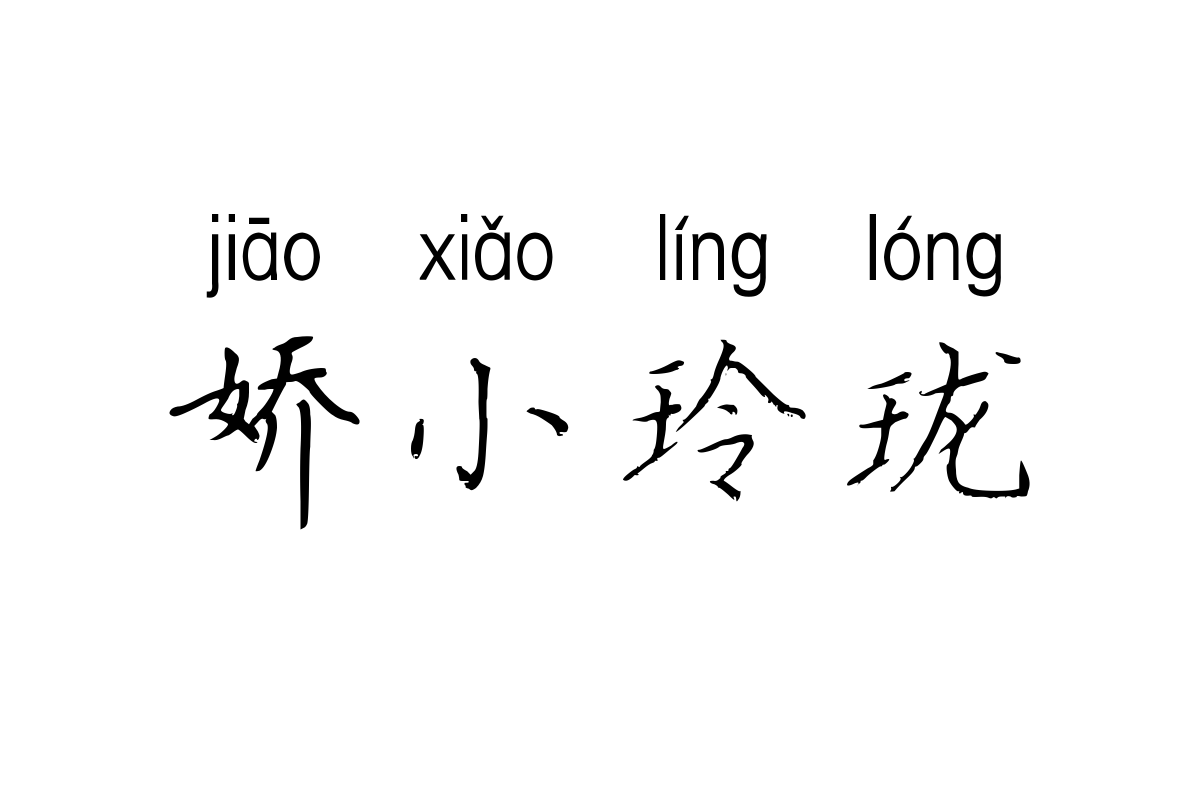
汉呈惊鸿楷书拼音体是一款由中国书法家创作的字体,其特点是笔画流畅,结构紧凑,具有很高的艺术价值。这款字体在设计上采用了传统的楷书风格,同时融入了现代的审美观念,使得字体既有古典的韵味,又不失现代的气息。
汉呈惊鸿楷书拼音体的主要特点如下:
1. 笔画流畅:这款字体的笔画线条流畅,没有过多的顿挫,给人一种轻松愉悦的感觉。
2. 结构紧凑:虽然笔画流畅,但每个字的结构却非常紧凑,没有多余的空间,使得整体视觉效果更加和谐统一。
3. 艺术性强:这款字体在设计上融入了书法艺术的元素,使得字体既有传统书法的韵味,又不失现代的艺术感。
4. 易于识别:由于笔画流畅且结构紧凑,这款字体在视觉上具有较高的辨识度,便于人们快速识别和记忆。
5. 适用范围广:这款字体适用于各种场合,如广告、宣传、印刷品等,具有很强的实用性和广泛的适用性。
总之,汉呈惊鸿楷书拼音体是一款极具艺术性和实用性的字体,适合用于各种需要展现传统文化魅力和现代审美追求的场合。